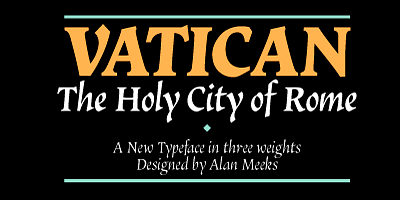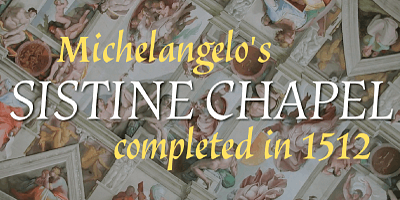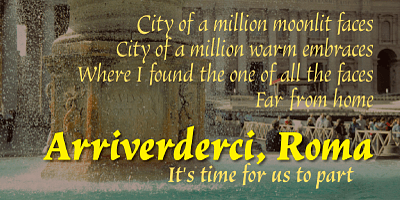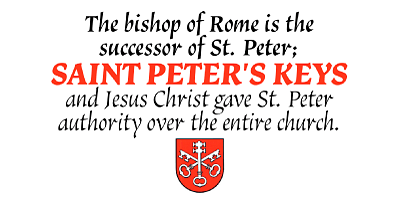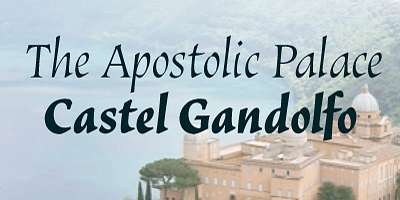
Vatican es un tipo de letra caligráfico. La minúscula está influencia de la letra de Arthur Baker, pero las mayúsculas son más formales, la forma de la V mayúscula me recordaba a la mitra de un obispo, lo que me llevó al nombre. El grosor más ligero funciona muy bien en piezas de texto pequeñas